字体本身就是艺术
不得不承认,随着电脑和手机输入的普及,人们写字的机会少了,对字体本身蕴涵的美感也越来越难以敏锐地捕捉。而在中国历史上,古人对书法的热爱孕育出大批的书法家和丰富多彩的汉字风格,这些极具视觉美感的字体本身就诉说着中华文化的瑰丽多姿。
6月23日~ 30日,“活字——文字的艺术世界”系列展在南京艺术学院举行。系列展包括第三届“字酷”文字艺术设计展、字道二O一八·南京站和“活字——文字的艺术世界”主题论坛,总共三个部分。从展览的名称即可看出,这场展览旨在通过设计语言对文字视觉形态的再塑,让字体“活”起来,“酷”起来(“字酷”即coolwords),让字体本身成为自足的“艺术世界”。
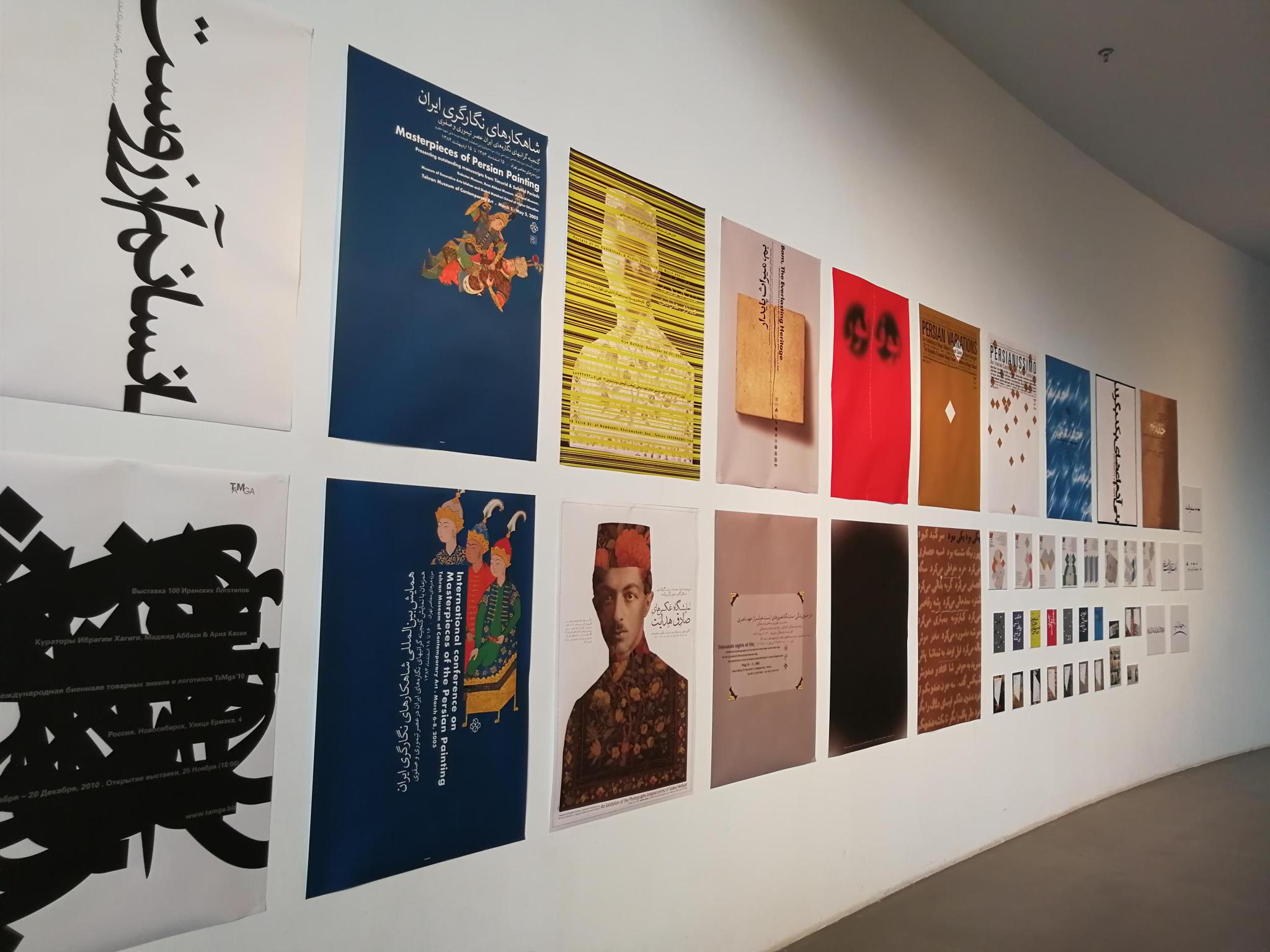
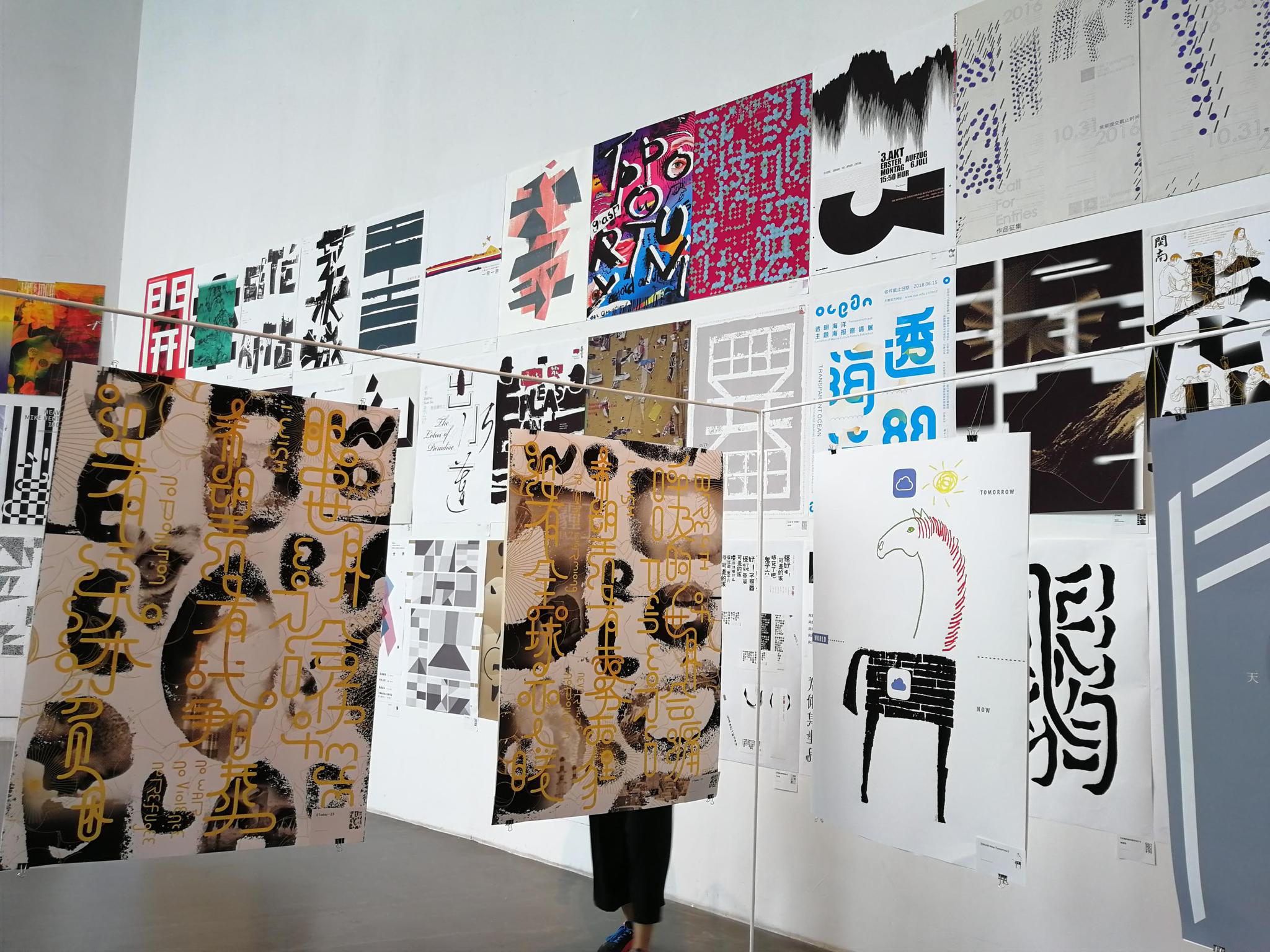
展览现场
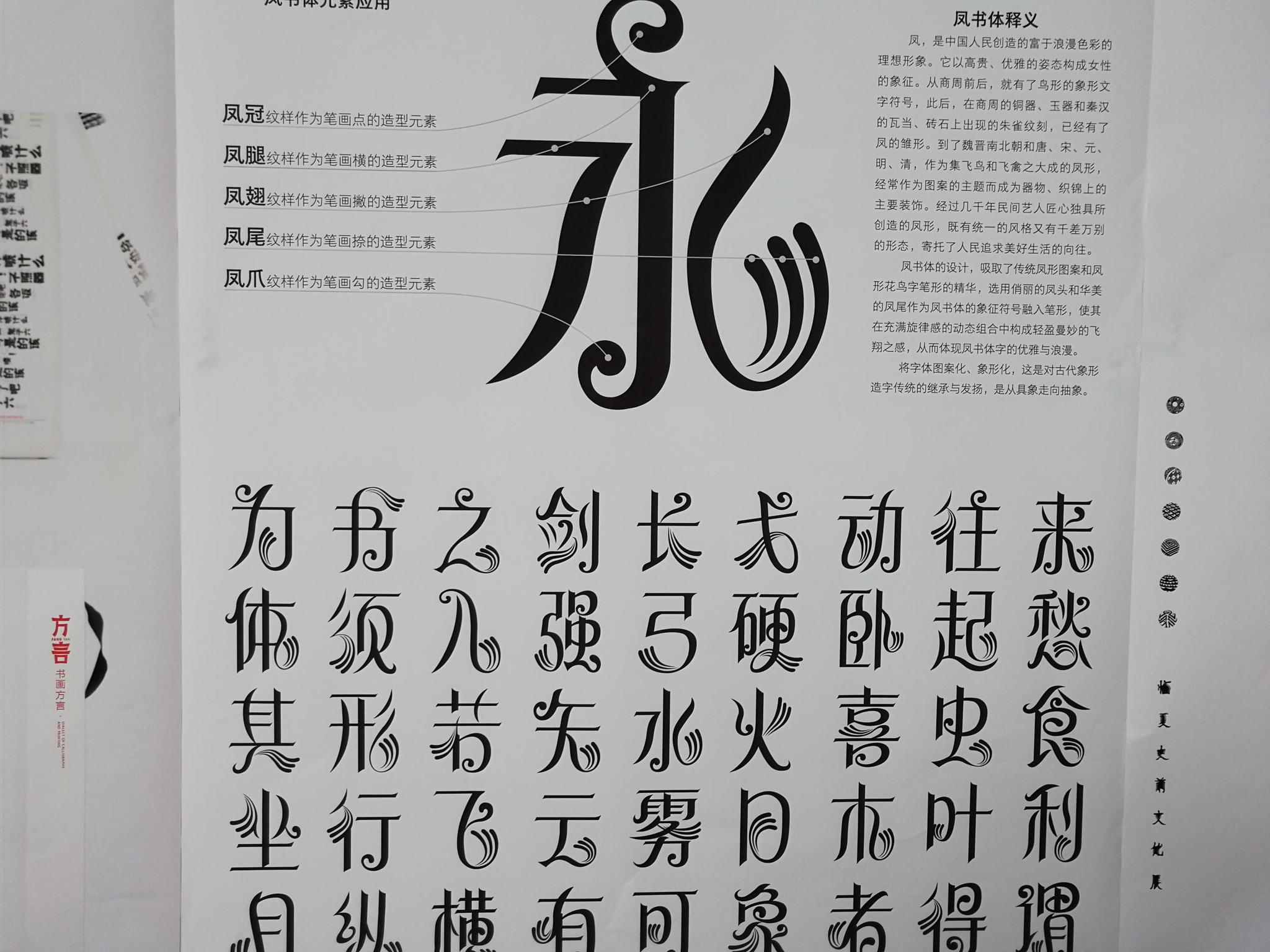
凤书体
字体是展示民族文化的窗口。这一由设计师创造的凤书体,吸取了传统凤形图案和凤形花鸟字笔形的精华,选用俏丽的凤头和华美的凤尾融入笔形,使其在充满旋律感的动态组合中构成轻盈曼妙的飞翔之感。话说,这字体的颜值简直不要太高啊!!!
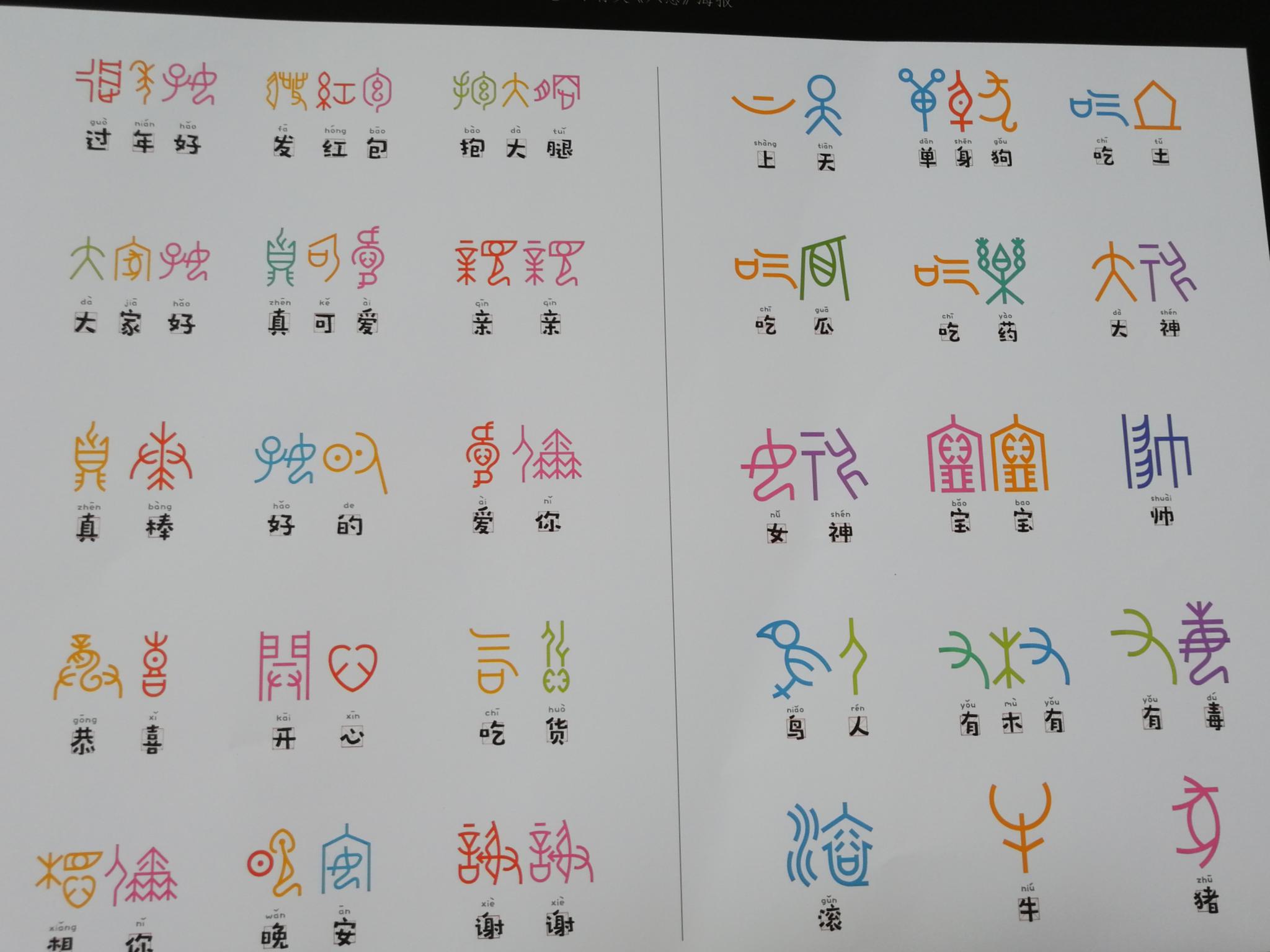
甲骨文表情包
这套《甲骨文表情包》已经上线啦!“亲亲”“真棒”“爱你”“抱大腿”......动动手指即可发送表情,用甲骨文说出你的爱~
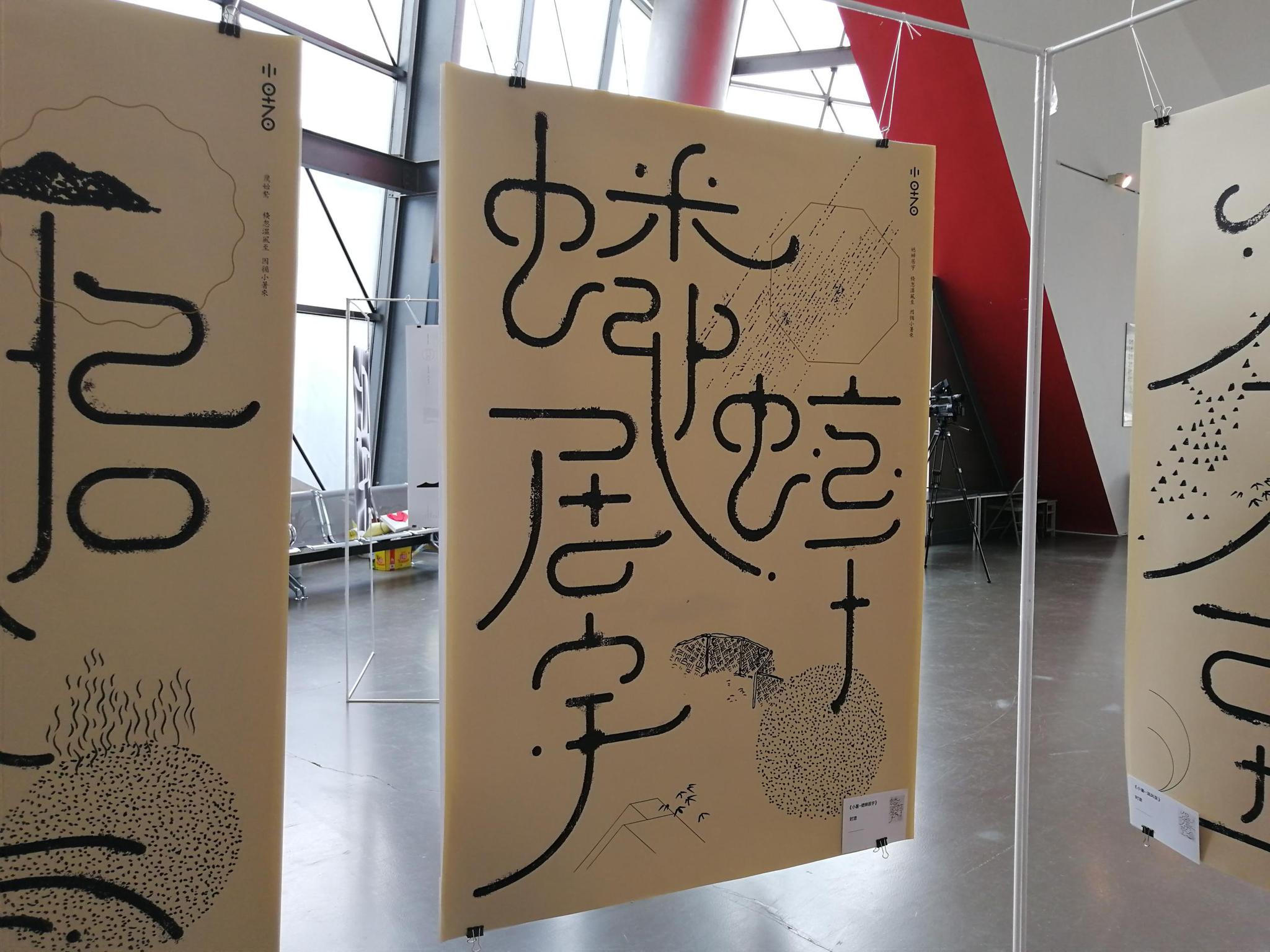
蟋蟀居宇
再过14天就要迎来二十四节气中的小暑。小暑分三候:一候温风至;二候蟋蟀居宇;三候鹰始鸷。这句话的意思是说,小暑时节,吹来的风不再是凉爽的,风中会夹着热浪。五日后,天气炎热,地表温度升高,蟋蟀也跑到岩壁下阴凉的地方乘凉避暑热。再过五日,老鹰则因地表高温,选择搏击长空,变得更加凶猛。这幅《蟋蟀居宇》展示的就是小暑节气中的第二候。
说起节气,这次展览中还有一幅萌萌的《立夏》:
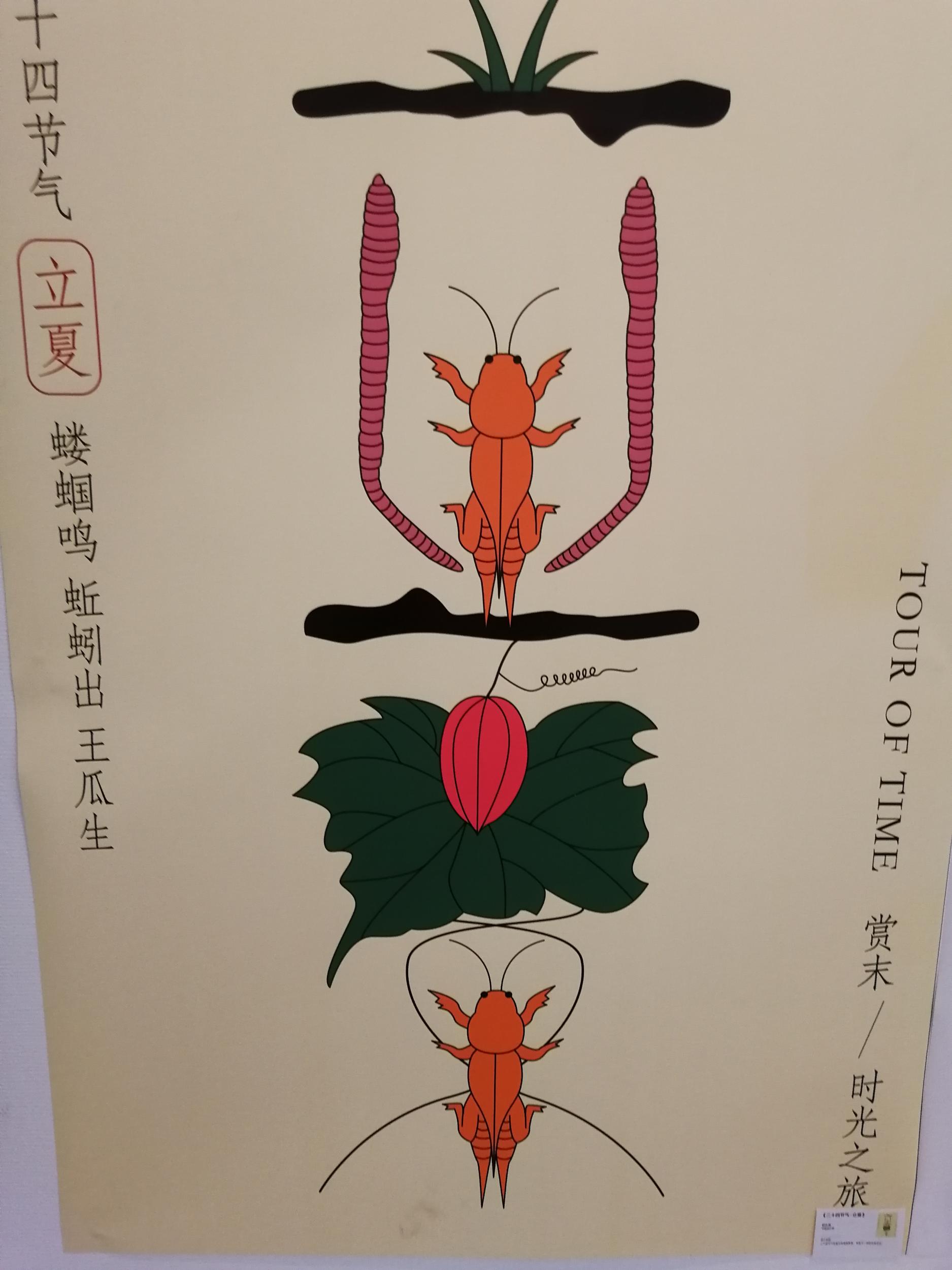
立夏
虽然二十四节气已经是世界级非物质文化遗产,但对于这些节气的含义,很多人并不清楚。立夏意味着夏天的开始,万物至此皆长大,故而蝼蝈鸣,蚯蚓出,王瓜生。这幅《立夏》巧妙地在“立夏”二字的笔画中运用蝼蝈、蚯蚓、王瓜的形象,让观众“秒懂”这一节气的特点。
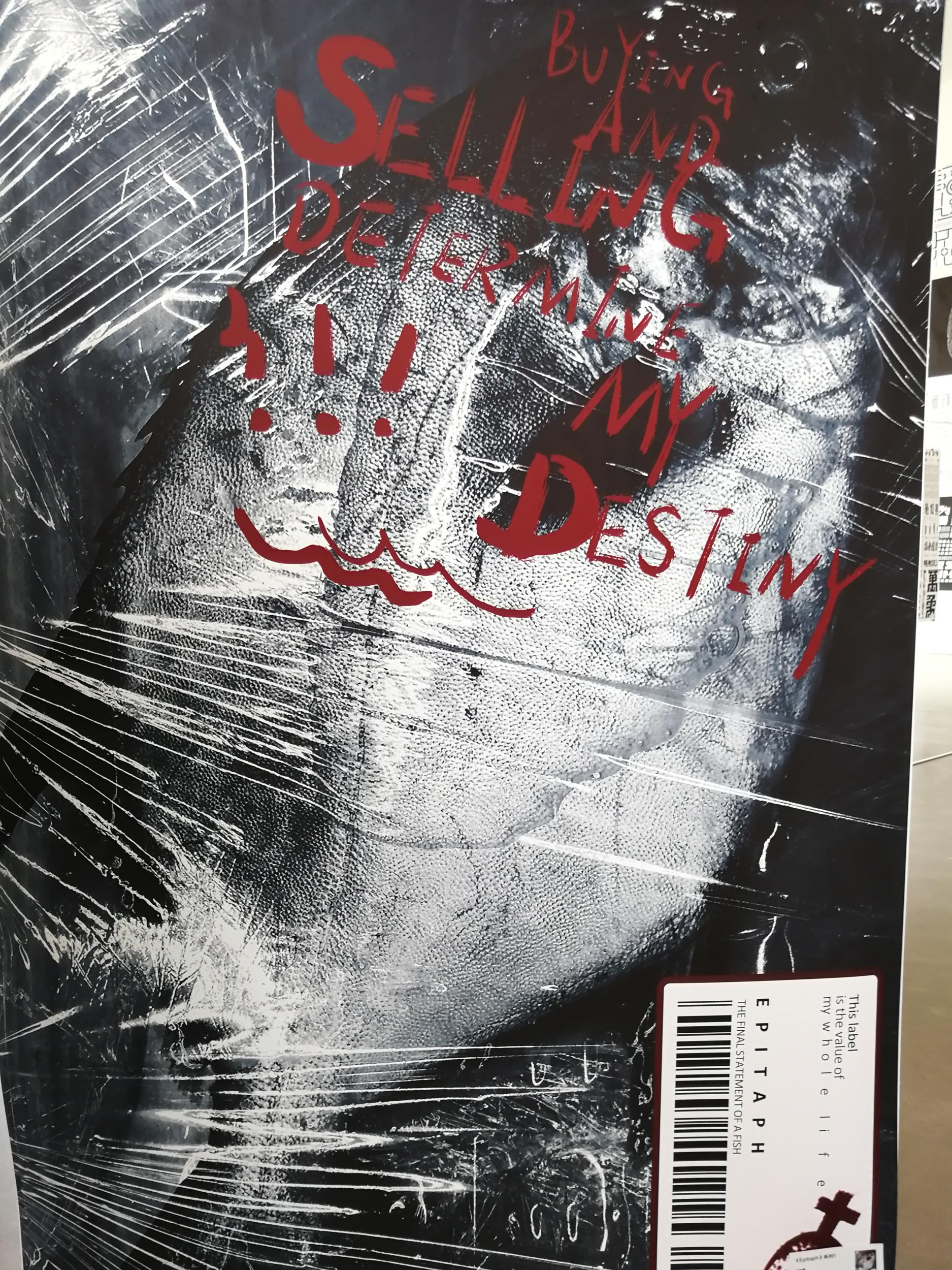
EPITATH(墓志铭)
抱慰生命、表达对世界和人生的反思,是艺术的使命。这幅EPITATH展示的其实是一件在超市售卖的生鲜商品,在表面覆着的保鲜膜上,设计师用触目惊心的红色字体,为这条生命写下墓志铭:Buying and selling determine my destiny.(我的命运就是被买卖)这句话是一条鱼最后留给世界最后的话语。
值得一提的是,此次展览特别邀请了两位来自中东的设计师携作品参展,分别是来自伊朗的Majid Abbasi和来自以色列的Oded Ezer,两位均为国际平面设计联盟AGI的成员。他们和中国的设计者一起,围绕着“一带一路”(One Belt One Road)主题进行相关的字体设计。
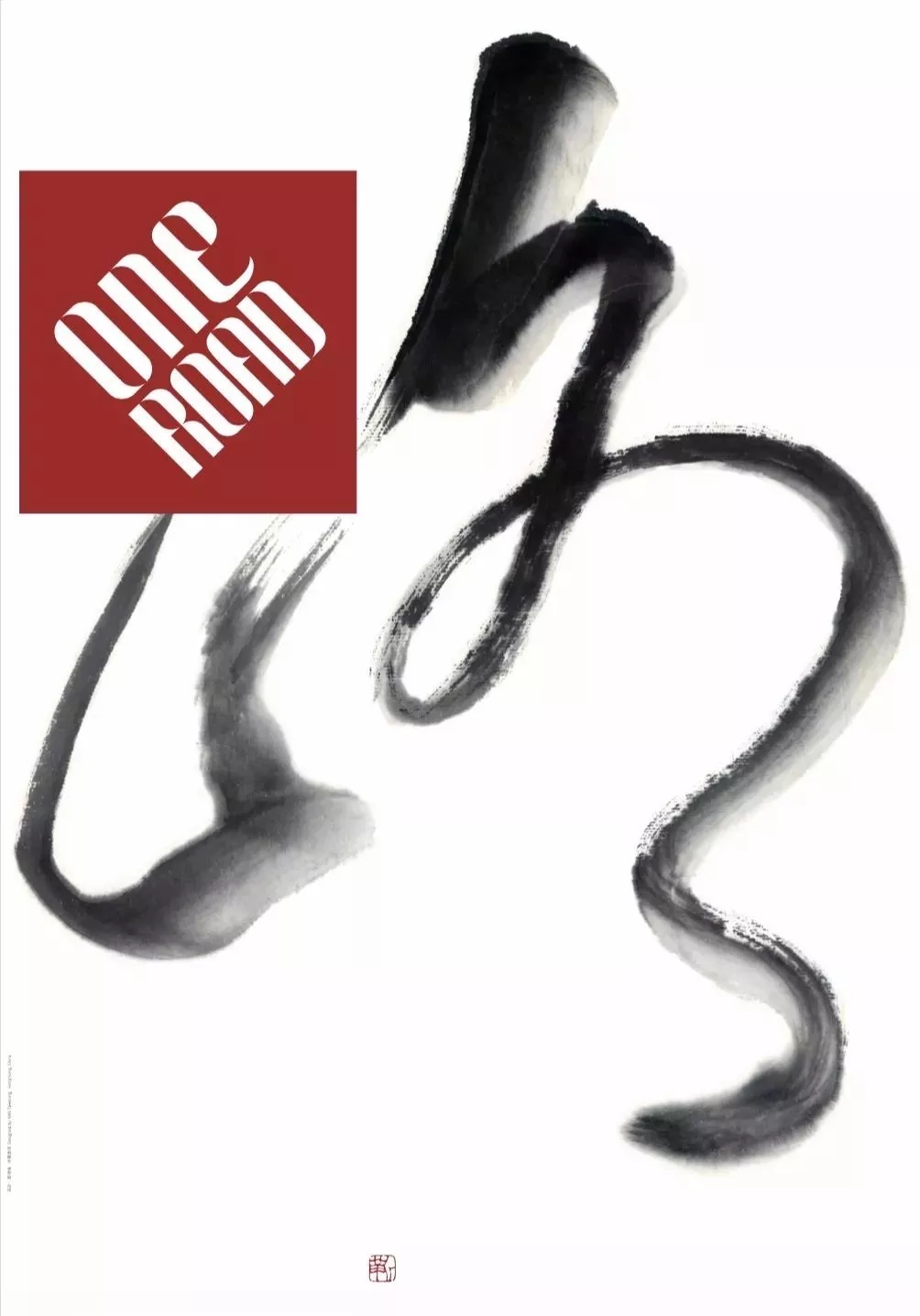
靳埭强作品《一带一路》
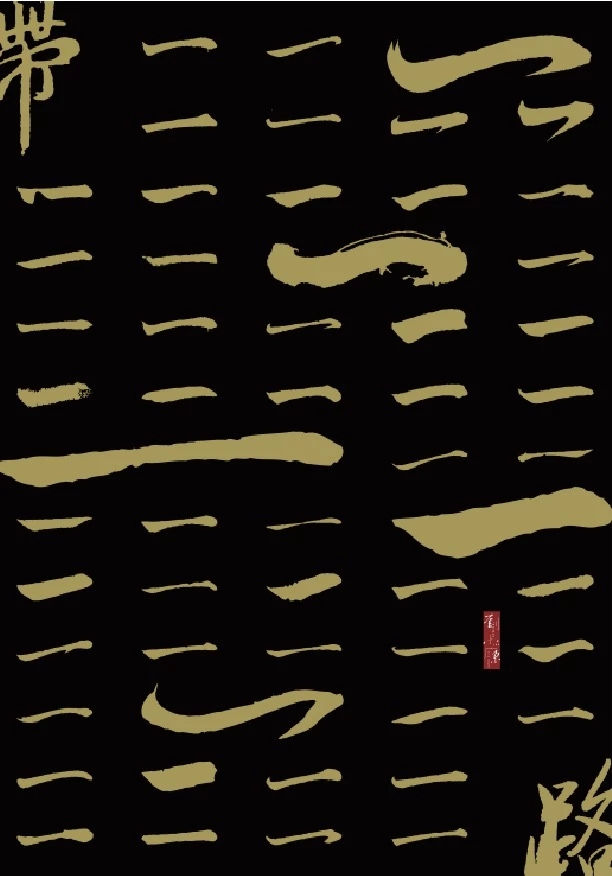
刘小康作品《一带一路》
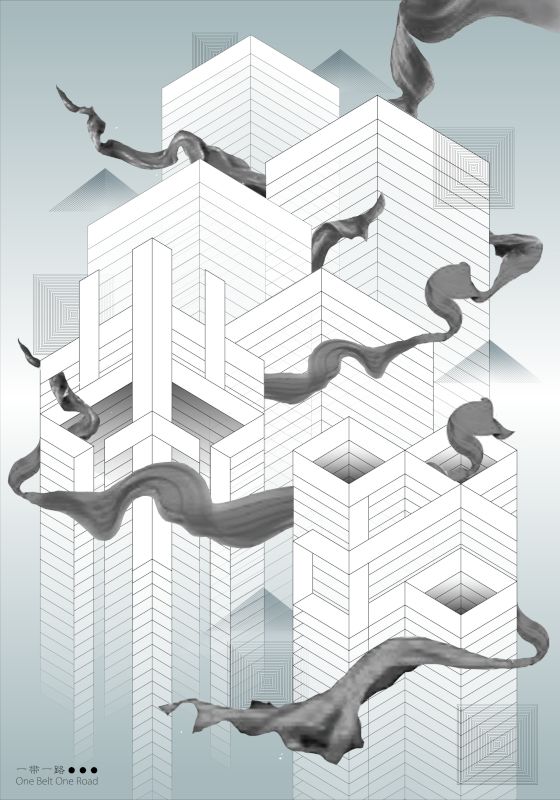
宋肖霏作品《一带一路》
在这幅作品中,如果说林立的高楼象征着现代化的中国,那么飞舞其间的丝绸则令人想起那条运输着丝绸、茶叶并促进了中西方文化交流的古丝绸之路,从整体的视觉呈现来说,沙漠又构成了画面的重要因素之一。作品似乎意在表明,孕育了古丝绸之路的中国将以更加繁盛、强大的姿态参与到和谐包容的全球化世界的构建中来。
此次展览的策展人、南京艺术学院教授曹方表示,文字艺术设计不仅具有信息传达这一基本的媒介功能,更重要的是,它也是最能体现历史、地域、民族、文化、身份的设计语言。可以说,一幅文字就是一扇通向民族深处的窗口。曹方作品《一带一路》